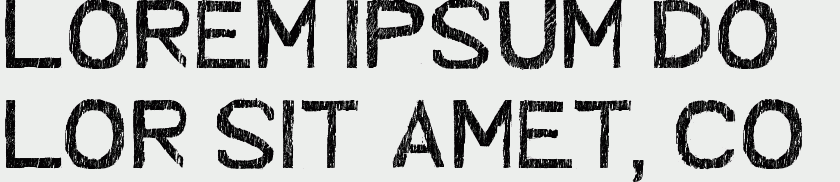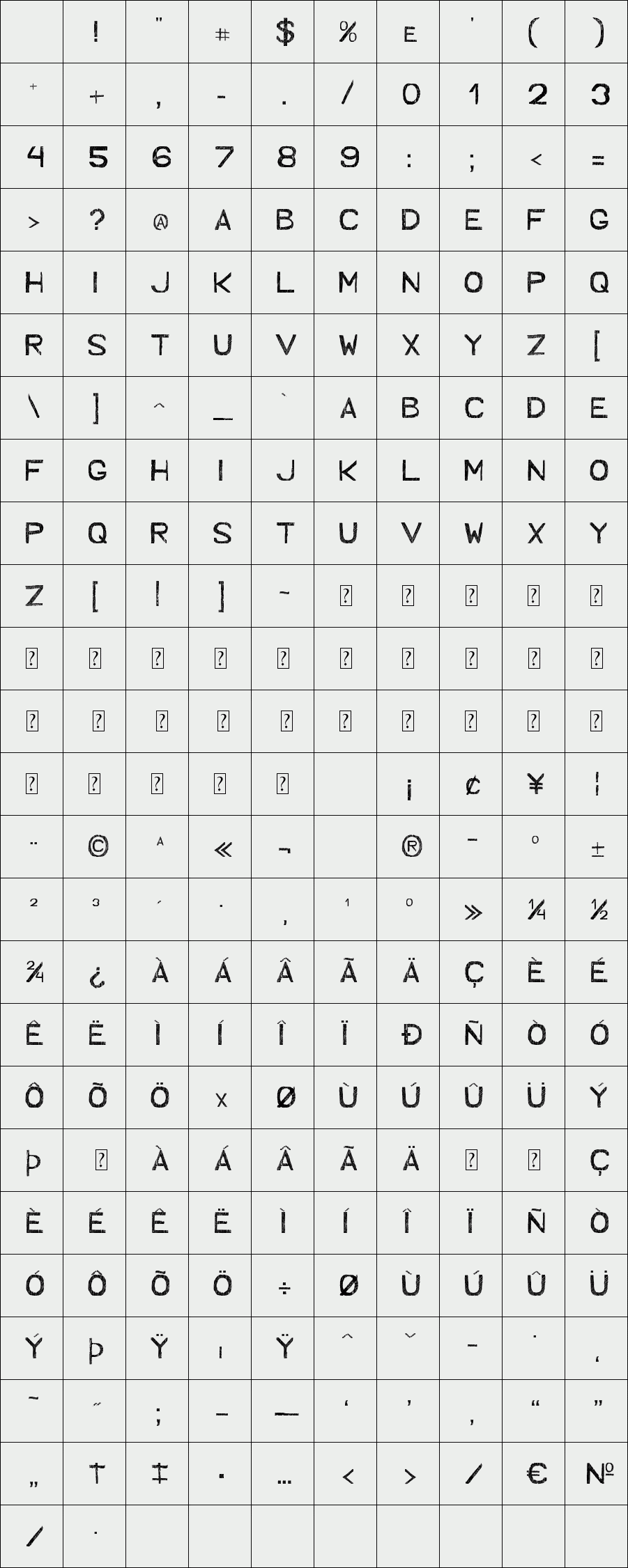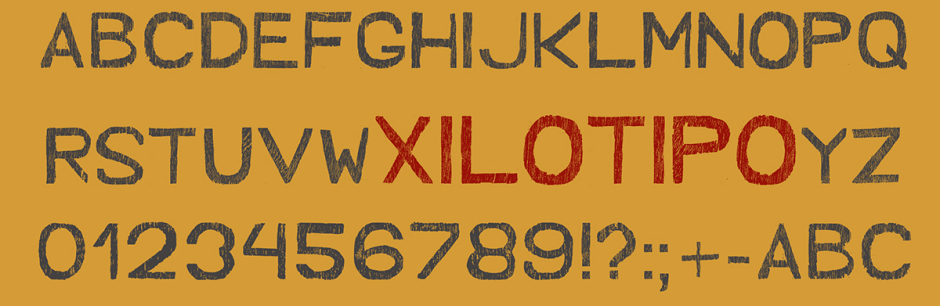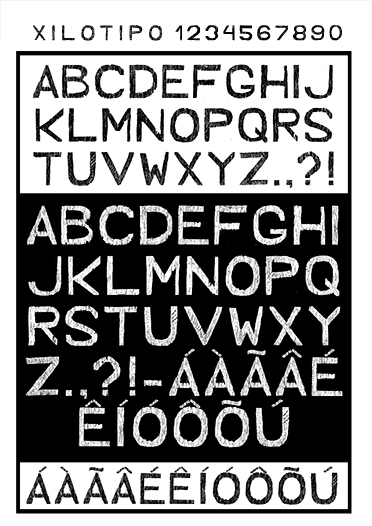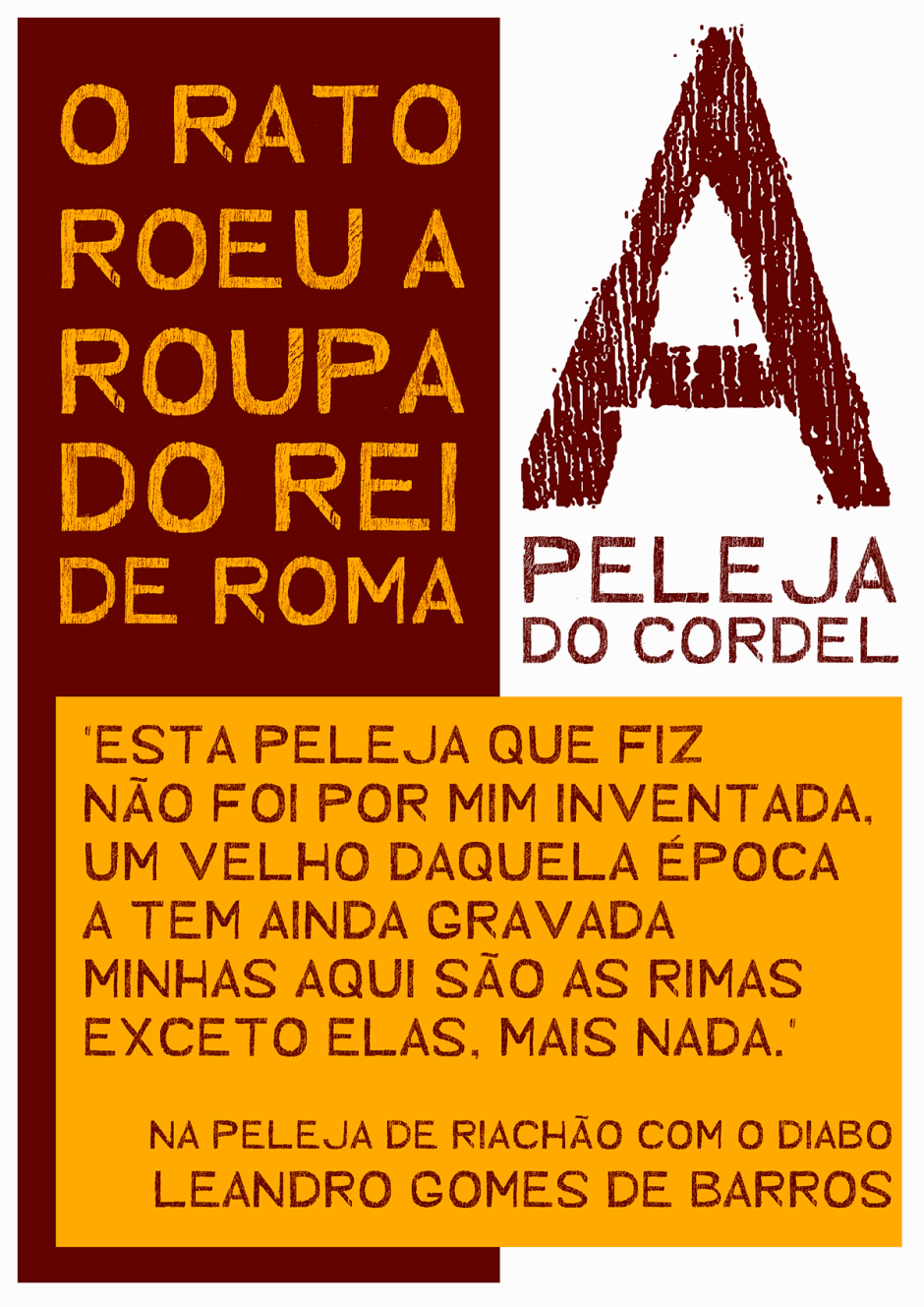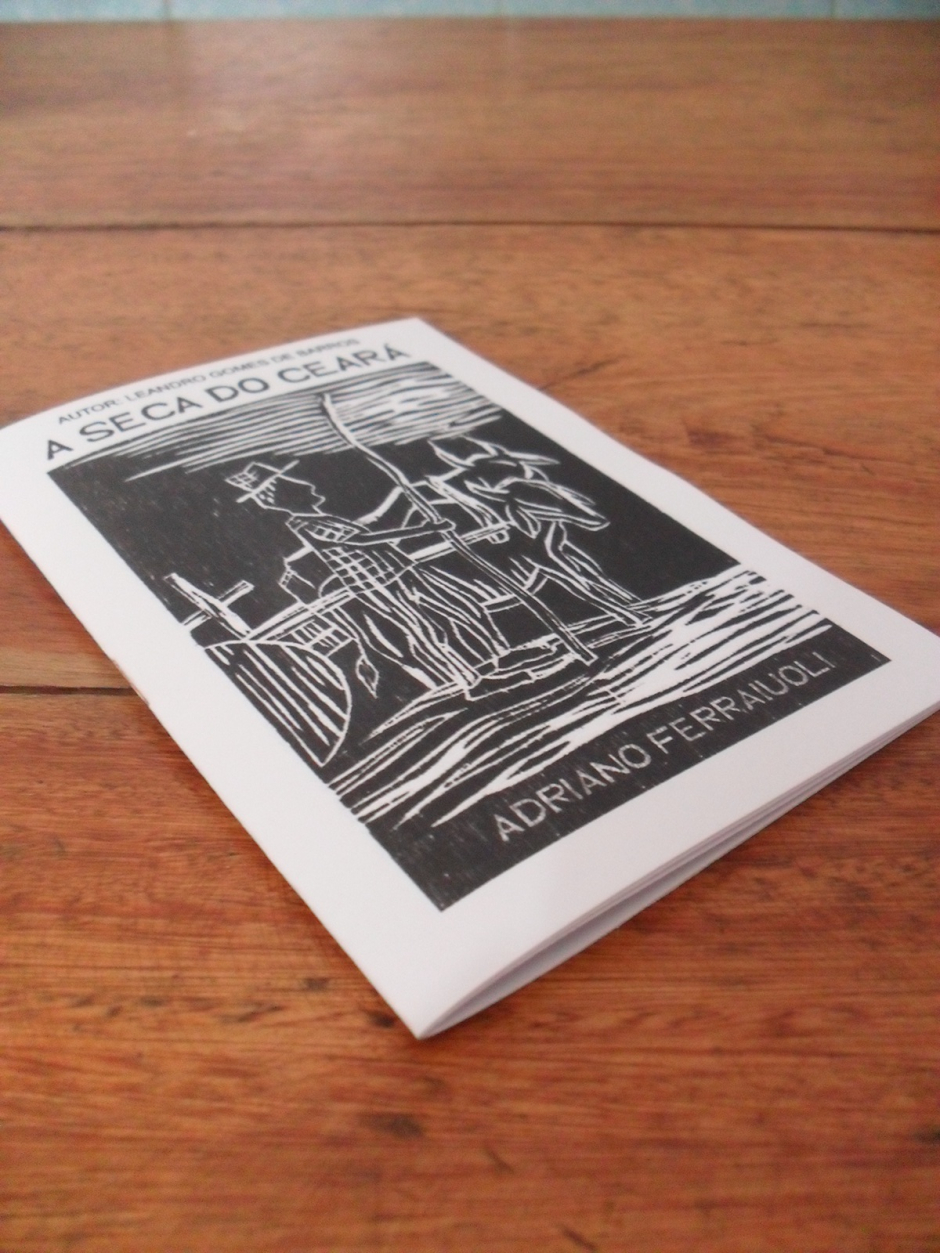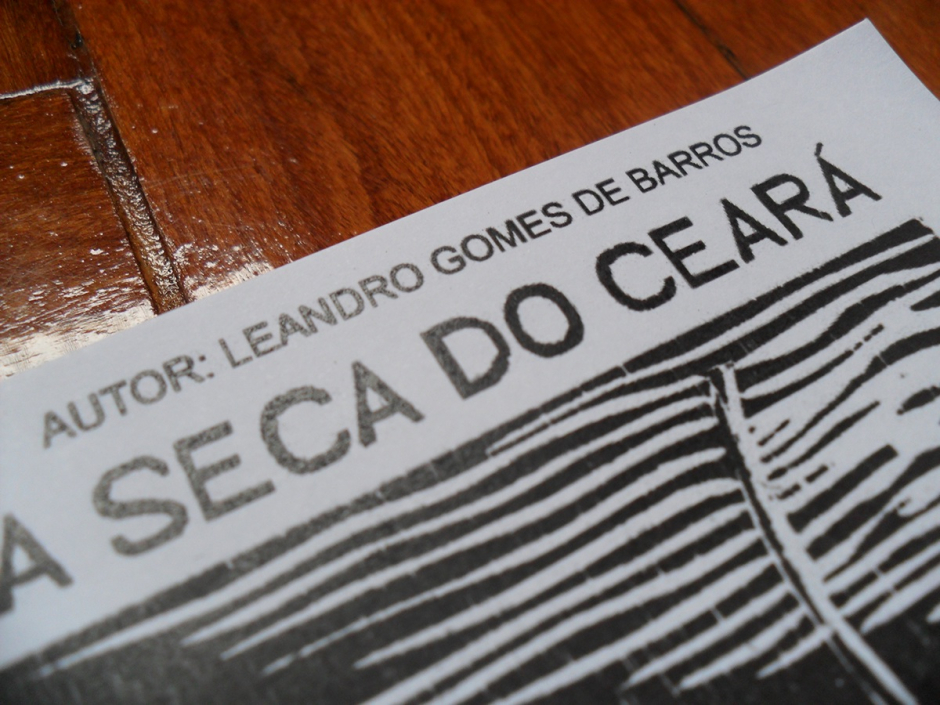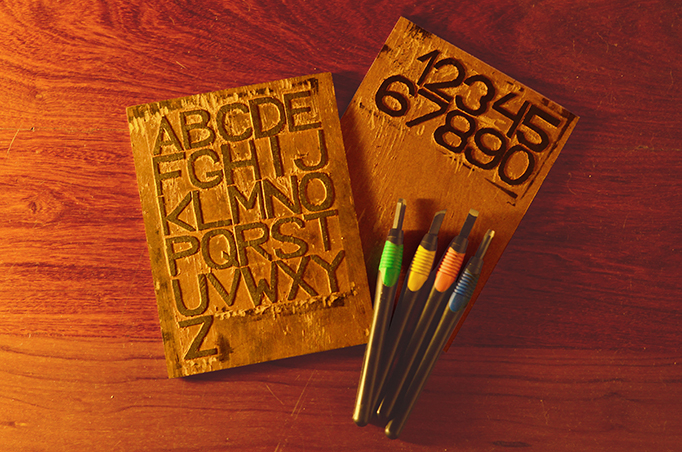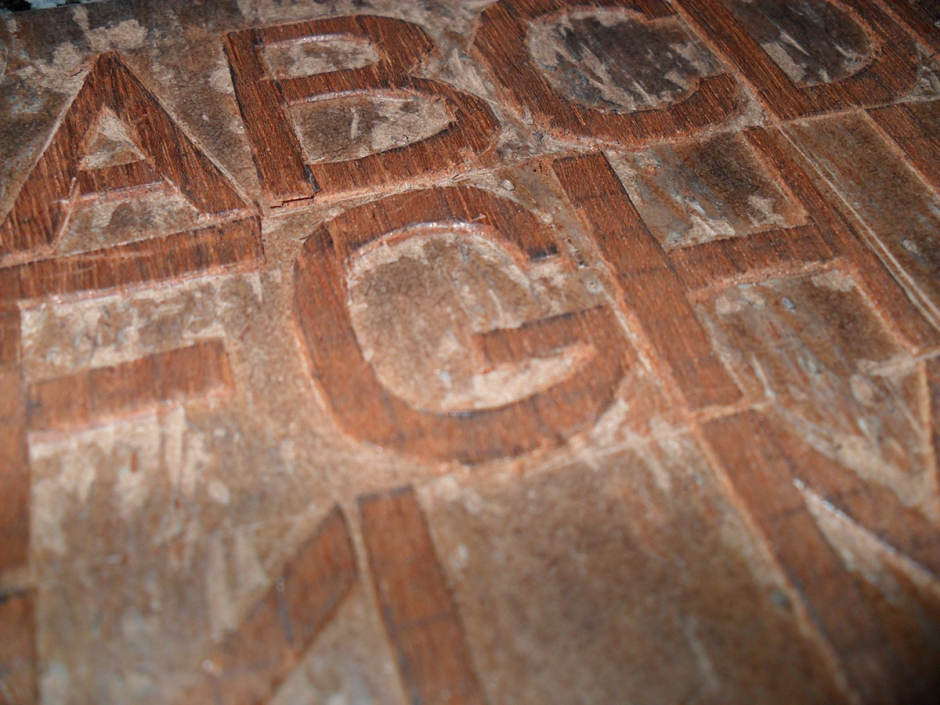
Xilotipo
The font was developed and printed in woodcut and then scanned and transformed into a font.
The project was developed in conjunction with the article The role of the designer in the promotion and rescue of the Brazilian woodcutting culture in typography, which was presented at CONGIC / CIDI 2013 (International Congress of Information Design) and later defended before the evaluating bank in the Course Superior of Technology in Graphic Design of the IFF (Federal Fluminense Institute).
A fonte foi desenvolvida e impressa em xilogravura e depois digitalizada e transformada em fonte.
O projeto desenvolveu-se em conjunto com o artigo O papel do designer na promoção e resgate da cultura xilográfica brasileira em tipografia, que foi apresentado no CONGIC/CIDI 2013 (Congresso Internacional de Design de Informação) e posteriormente defendido perante a banca avaliadora no Curso Superior de Tecnologia em Design Gráfico do IFF (Instituto Federal Fluminense).
The project was developed in conjunction with the article The role of the designer in the promotion and rescue of the Brazilian woodcutting culture in typography, which was presented at CONGIC / CIDI 2013 (International Congress of Information Design) and later defended before the evaluating bank in the Course Superior of Technology in Graphic Design of the IFF (Federal Fluminense Institute).
A fonte foi desenvolvida e impressa em xilogravura e depois digitalizada e transformada em fonte.
O projeto desenvolveu-se em conjunto com o artigo O papel do designer na promoção e resgate da cultura xilográfica brasileira em tipografia, que foi apresentado no CONGIC/CIDI 2013 (Congresso Internacional de Design de Informação) e posteriormente defendido perante a banca avaliadora no Curso Superior de Tecnologia em Design Gráfico do IFF (Instituto Federal Fluminense).
Designer: Cleyton Souza Nunes